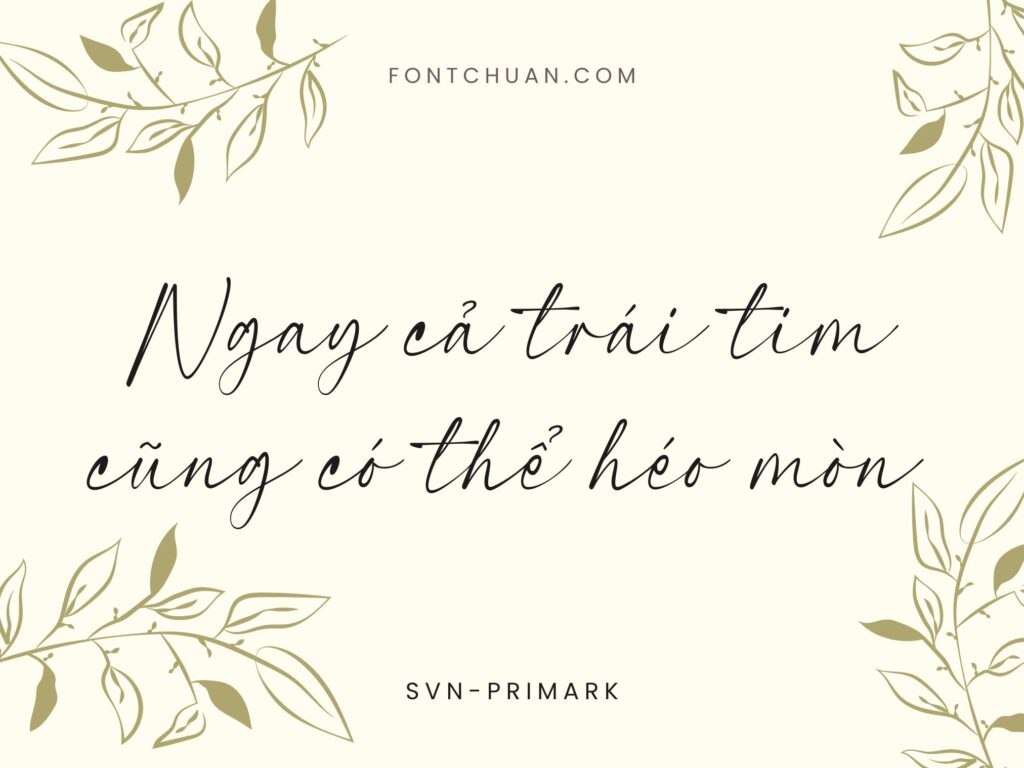
Font SVN Primark Việt Hóa
Font SVN Primark là phiên bản Việt hóa của kiểu chữ Primark, được thực hiện bởi STYLEno.1 Fonts. Đây là một kiểu chữ script mang phong cách thư pháp hữu cơ, được thiết kế bởi Cititype. Primark nổi bật với sự kết hợp giữa vẻ đẹp cổ điển và sự tinh tế của thiết kế hiện đại, tạo nên một phong cách đặc biệt và ấn tượng. Font này bao gồm ba biến thể: Regular, Alternate và Swash, cho phép người dùng linh hoạt trong thiết kế. Primark hỗ trợ đầy đủ các ký tự chữ hoa, chữ thường, chữ số và dấu câu, cùng với các ligature tự nhiên và hỗ trợ đa ngôn ngữ. Font này phù hợp cho nhiều mục đích sử dụng khác nhau như thiết kế logo, chữ ký số, danh mục đầu tư trực tuyến, biểu ngữ trang web, áp phích, thiệp mời đám cưới và tiêu đề sách.
SVN Primark lý tưởng cho các dự án thiết kế yêu cầu sự thanh lịch và hiện đại, như thiết kế logo, tiêu đề, bao bì sản phẩm và các ấn phẩm truyền thông. Các ngành nghề như thiệp cưới, giáo dục và bất động sản có thể tận dụng font này để tạo điểm nhấn trong thiết kế. Ngoài ra, font cũng thích hợp cho các sự kiện như Tết, Valentine, Sinh nhật và các lễ hội khác.